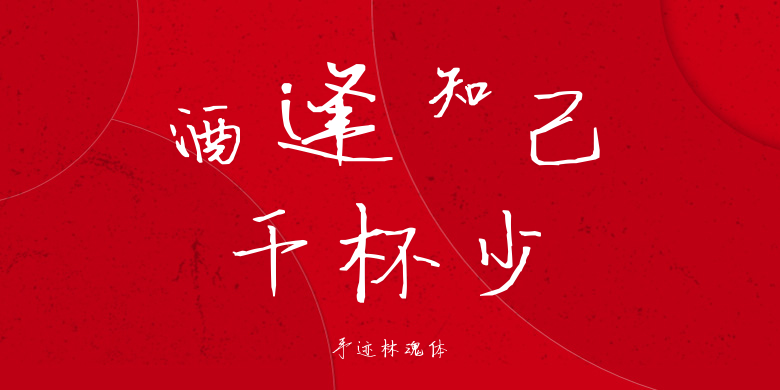
手迹林魂体
手迹林魂体,这款字体结构工整、笔画清晰,兼顾美观与易读性,适用于标题、正文、海报、包装、LOGO 等多种场景。字形优雅稳定,风格百搭耐看,适配日常排版与创意设计,让文字呈现更舒适、更具质感。手迹林魂体一笔一画,皆是细节,以均衡的比例、流畅的线条打造舒适视觉体验,字形端正大气,风格简约现代。无论是商业设计、品牌宣传还是日常排版,都能轻松驾驭,让文字更有格调与力量。手迹林魂体字体下载。